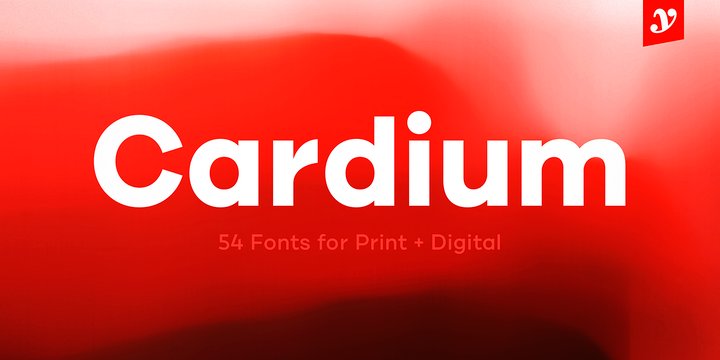
Myfonts Cardium Font
[Myfonts] Cardium Font
Кардиум - это трудолюбивый 54-шрифтовой современный геометрический безель.
Он универсален, чист, разборчив и слегка диссидентский.
Кардиум разделяет большую часть своей ДНК с нашим набором Драфтового типа, но является более утилитарным. Это обширное семейство с девятью весами от Hairline до Black и тремя ширинами - с наиболее удлиненной буквой "A", буквой "B", имеющей традиционные пропорции кузова, и буквой "C", мягко сжатой для тех времен, когда пространство находится в премиум-классе. Она предлагает полный набор профессиональных шрифтовых функций и обширную языковую поддержку.